Hadd kezdjem egy vallomással: Szeretem betűtípusokat. Saját gyűjtemény hatalmas, és ez az elegáns „kézzel írt” font és betűk emlékeztet egy stencil. De a leginkább figyelemre méltó - az is, hogy én teremtettem magamnak. Ez a folyamat ...
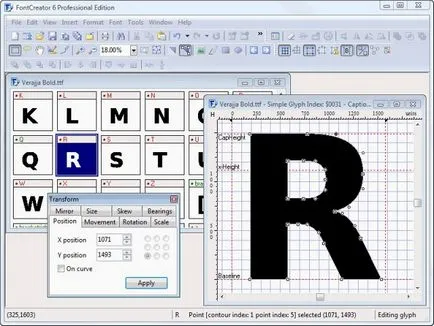
Hadd kezdjem egy vallomással: Szeretem betűtípusokat. Saját gyűjtemény hatalmas, és ez az elegáns „kézzel írt” font és betűk emlékeztet egy stencil. De a leginkább figyelemre méltó - az is, hogy én teremtettem magamnak. Ez a folyamat egyszerűbb, mint amilyennek látszik; hogy hozzon létre egy font igényel csak egy kis szabad ideje, egy speciális program (pl FontCreator Home edition cég Nagy-Logic, az USA-ban az ár közvetlen szállítások 79 $., www.high-logic.com) és egy szkenner.
1. nyomtatás szöveges formában. FontCreator a program futtatásához válassza a Fájl menü Új betűkészlet és hozzá az új betűtípus nevét.
Látni fogja, egy sor sejtek, az egyik az egyes betűk, számok és írásjelek. Ezek az úgynevezett képek (betűképeket) karakter. Nem kell, hogy töltse ki az összes sejtek (több mint 600, és sokan közülük akkor valószínűleg tartja felesleges), de jobb, ha túlzásba egy kicsit, mint kihagyni valamit; Nem lenne szégyen, ha kell újra beolvasni csak annak a ténynek köszönhető, hogy már találtak néhány nyilat vagy kiemelő felesleges.
Nyomtassa ki az űrlapot (szürke színnel jelennek meg a karakterek nem nyomtathatók ki, hanem ezen az oldalon maradni elég üres cellák). Most átvizsgálja a kézzel írt lapokat.
3. Beállítás. Kitöltése font asztal, és alaposan nézni, hogy pontosan hol van minden karakter. A legtöbb karakter kerülnek egy úgynevezett referencia vonalat. Az ilyen karaktereket G, J és Y, részlegesen bemennek a referencia vonalat. Minden szimbólum foglalják el a megfelelő helyzetben a vonatkoztatási vonal. Ezen túlmenően, a karakterek nem kell túllépni a határt körülhatárolt fekete vízszintes és függőleges koordináta vonalak. Ha szükséges, mozgassa a vonalat úgy, hogy a szimbólum ebben a keretben volt a megfelelő távolságot a többi karakter a táblázatban. Zárja le a kép a cella és ismételje meg a műveletet az összes maradék betűket, számokat és karaktereket a font.
4. Add díszítéssel. Ahhoz, hogy hozzon létre egy kép egy komplex jellegű, mint az e akut (e), hogy hozzon létre egy kisbetűs e és kiemelő jelet, amely áll a karakter. Kattintson a jobb gombbal a képre, eacute sejt és a megnyíló menüben válassza a Teljes kompozitok (ez a funkció csak a Professional kiadás változata, az amerikai ár közvetlen, $ 149); ennek eredményeként a két elem automatikusan összevonásra. Ehhez a művelethez manuálisan nyissa meg a megfelelő mezőbe a Beszúrás menüben válasszuk Glyph elemet, és válassza ki az első karaktert. Ismételjük meg a műveletet, és helyezze a második karaktert, majd helyezze őket a kívánt helyre egymáshoz képest.